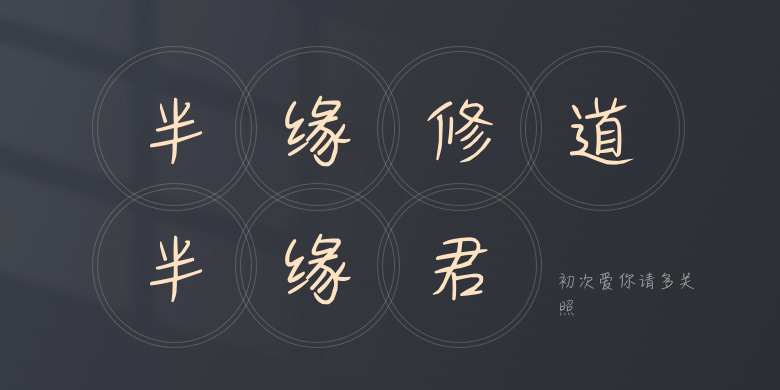
初次爱你请多关照
初次爱你请多关照,这款字体结构工整、笔画清晰,兼顾美观与易读性,适用于标题、正文、海报、包装、LOGO 等多种场景。字形优雅稳定,风格百搭耐看,适配日常排版与创意设计,让文字呈现更舒适、更具质感。初次爱你请多关照一笔一画,皆是细节,以均衡的比例、流畅的线条打造舒适视觉体验,字形端正大气,风格简约现代。无论是商业设计、品牌宣传还是日常排版,都能轻松驾驭,让文字更有格调与力量。初次爱你请多关照字体下载。